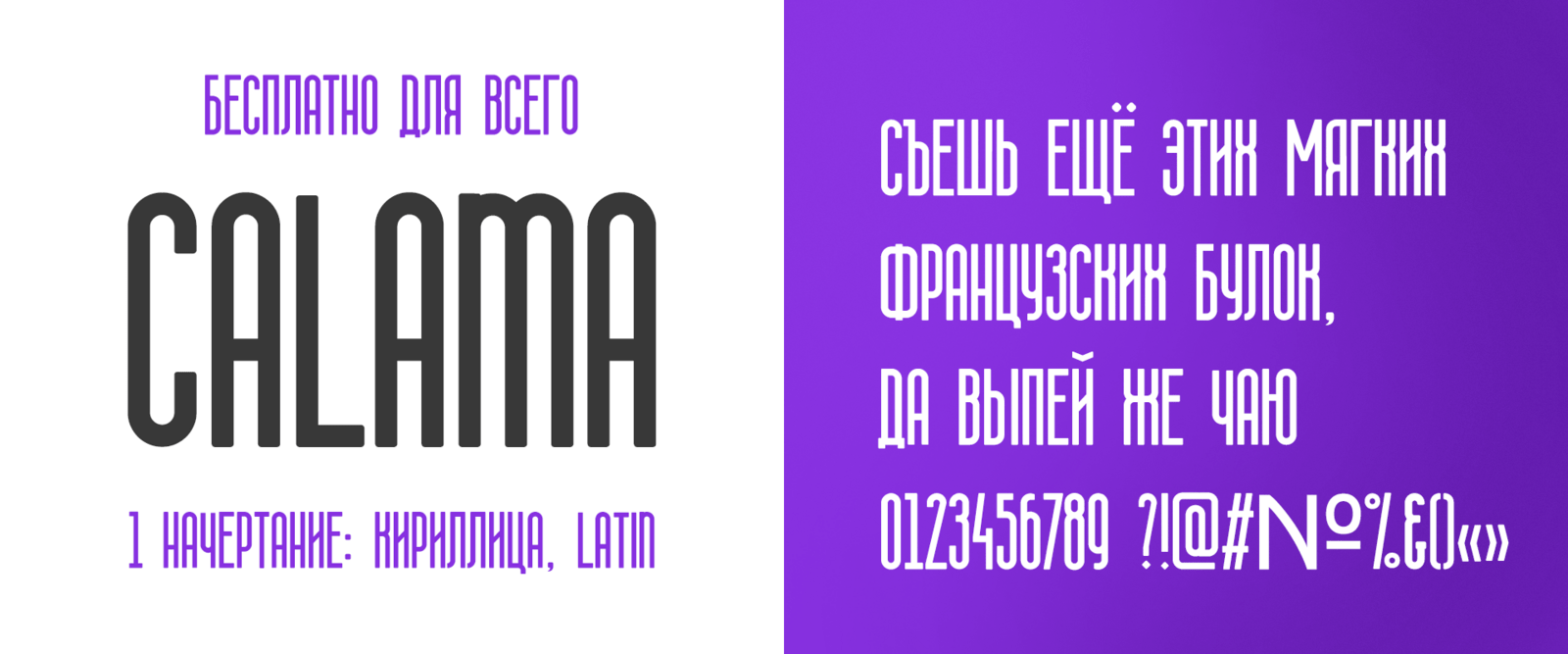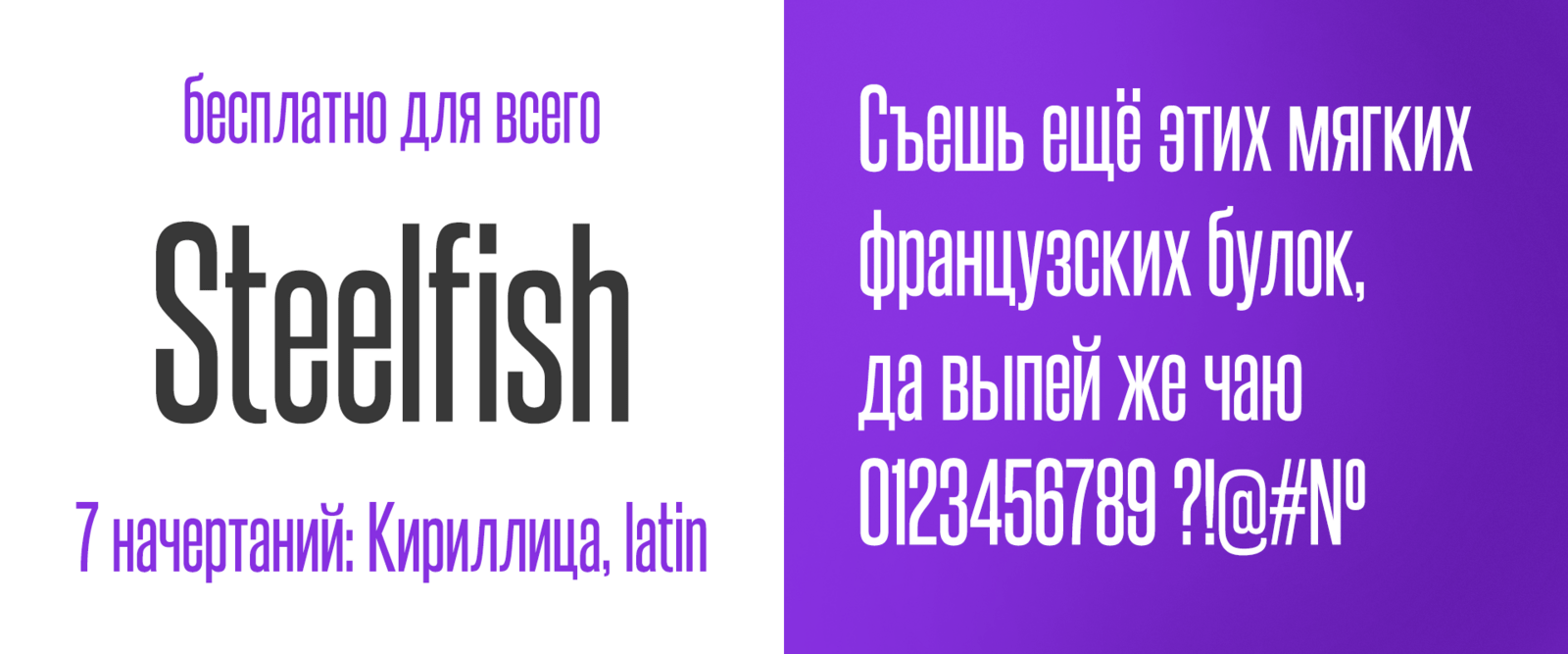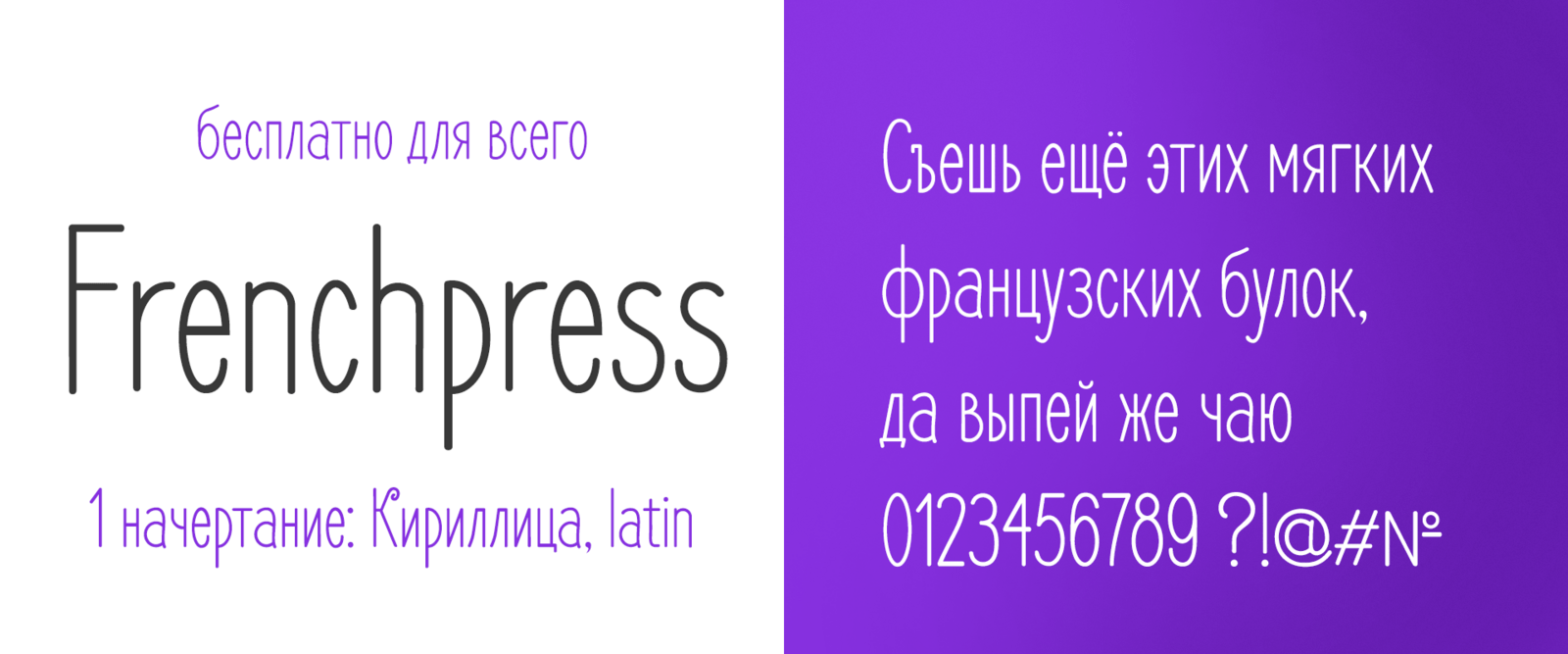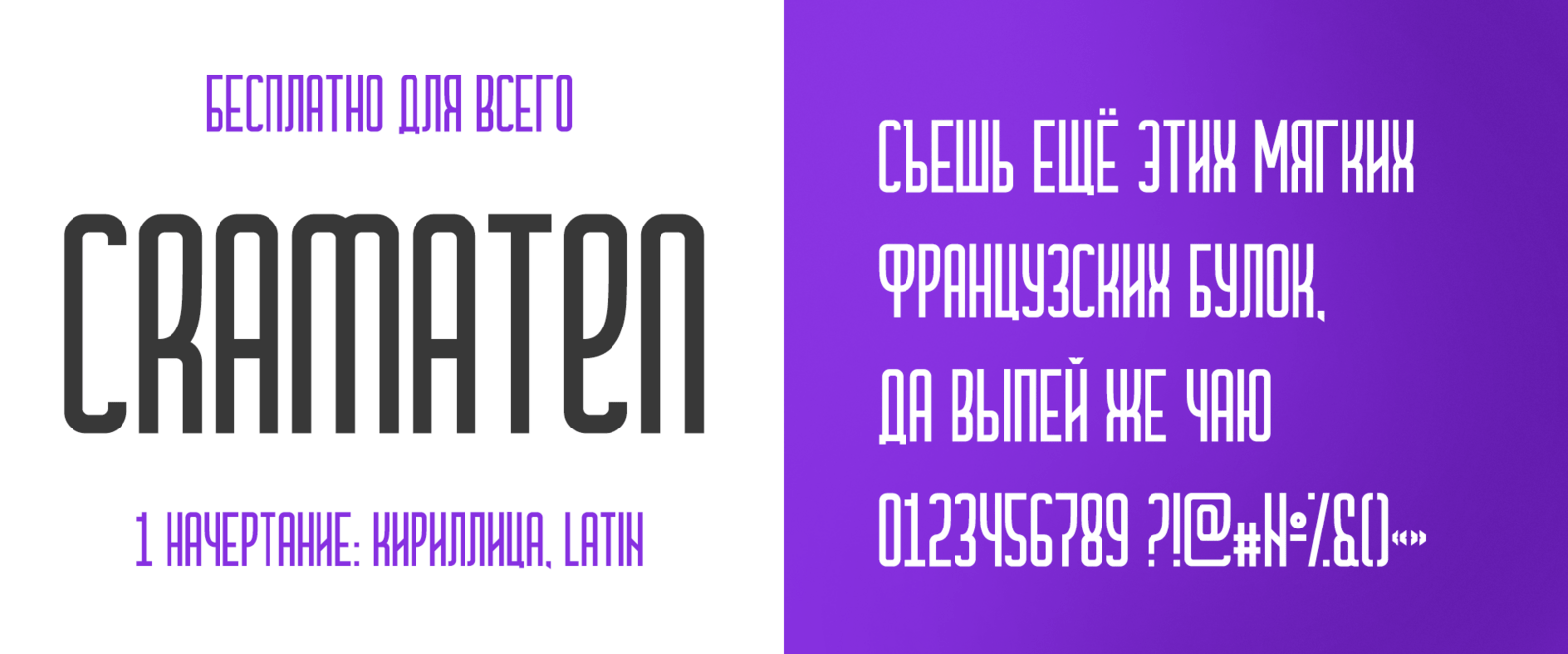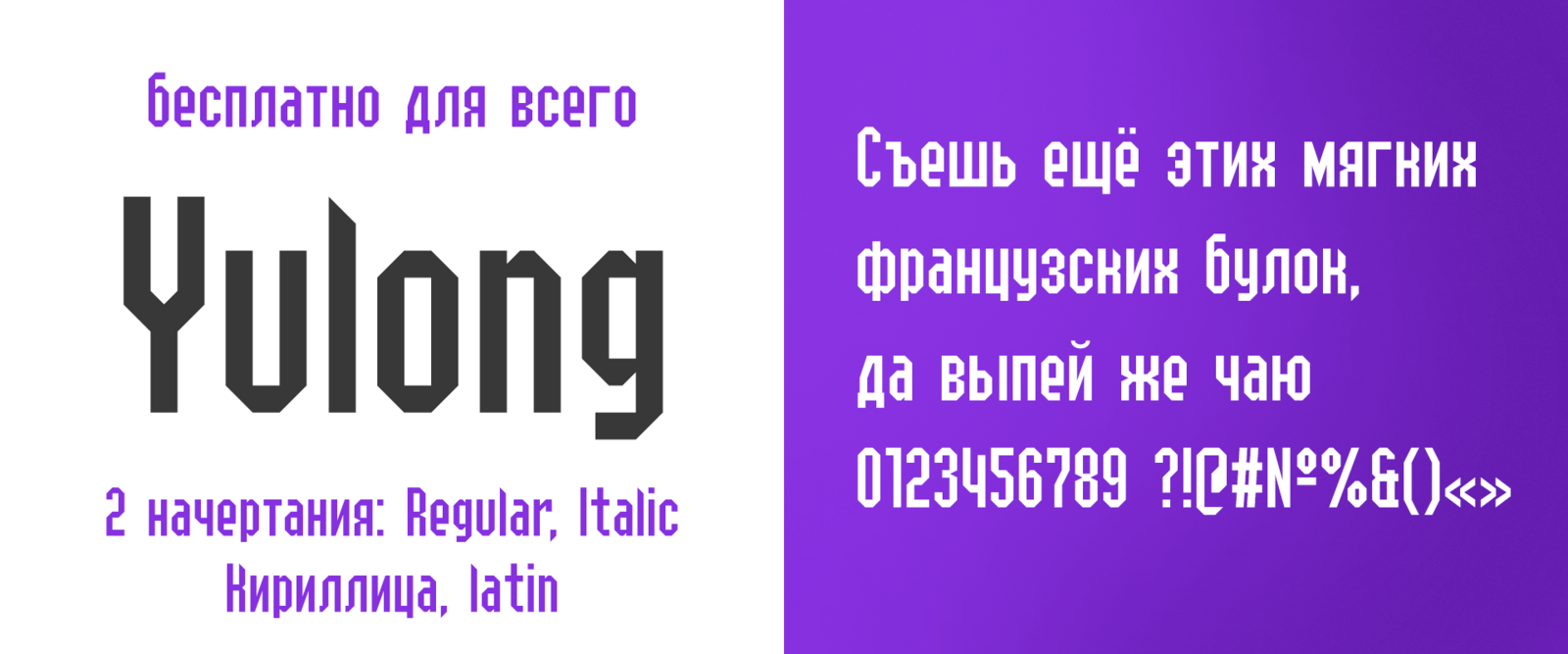
⚡️5 ШРИФТОВ ДЛЯ ТЕХ, КТО УСТАЛ ОТ BEBAS И DRUK CYR
Calama
Универсальный геометрический шрифт без засечек с закругленными углами. Подойдет не только для заголовков, но также для логотипов, значков и других креативных дизайнов в любом проекте.
Cramaten
Просто хороший сжатый шрифт с поддержкой кириллицы. Подойдёт для заголовков, надписей под фото, а также товаров для дома.
Yulong
Индустриальный шрифт. Отлично подходит для логотипов, крупных заголовков, плакатов, вывесок, принтов, а также макетов, связанных с технологиями и киберспортом.
Steelfish
Стильный сжатый шрифт, вдохновленный заголовками газет начала и середины 20-го века. Steelfish представляет собой уникальное сочетание различных шрифтов заголовков, поэтому он легко украсит любой ваш проект!
Frenchpress
Простой и понятный рукописный шрифт. Подходит для открыток, этикеток, писем, а также для оформления цитат.